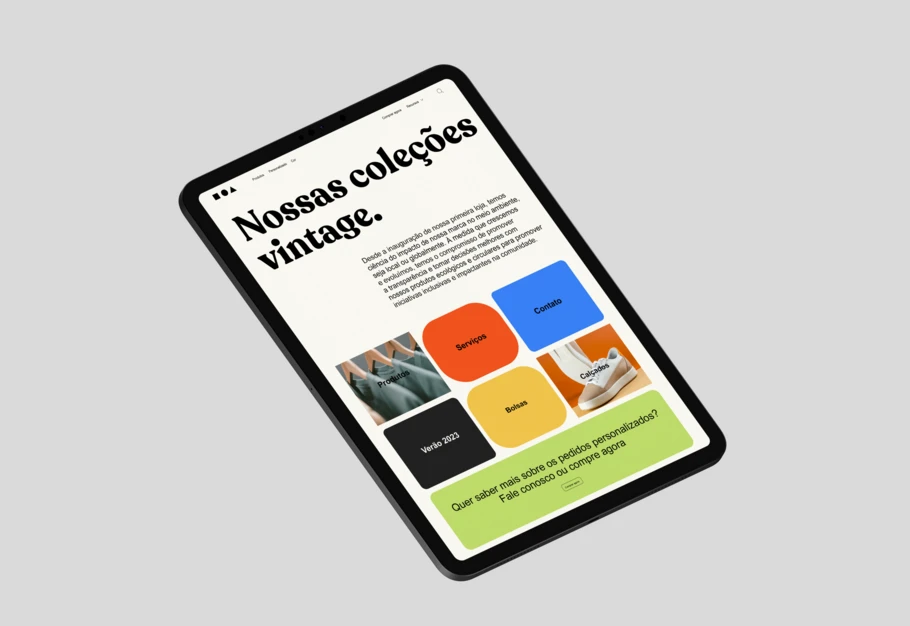
Sem confusão: cinco maneiras de manter sua marca prosperando na era digital.
À medida que os consumidores alternam entre telas grandes e pequenas, é fundamental que as marcas acompanhem essa dinâmica.
Sem confusão: cinco maneiras de manter sua marca brilhando na era digital.
Suas fontes de marca podem fazer a transição perfeita do ambiente físico para a Web? Suas fontes são legíveis em um aplicativo? E quanto a anúncios ou banners digitais? Ou um novo ambiente, como o metaverso, por exemplo?
Tornar a presença omnicanal de uma marca e a transformação digital coesas em todas as plataformas não é uma tarefa fácil, seja produzindo uma página da Web, um anúncio digital, um aplicativo, uma experiência de realidade virtual ou um novo jogo em uma arena virtual.
À medida que os consumidores alternam entre telas grandes e pequenas, é fundamental que as marcas acompanhem essa dinâmica. A escolha da fonte desempenha um papel fundamental. Afinal, uma presença de marca consistente em todos os pontos de contato mantém o nível de confiança alto e cria uma experiência agradável para o cliente.
Então, da próxima vez que você estiver trabalhando em um design para o mundo moderno, use esta lista de verificação para garantir que suas fontes estejam à altura da era digital – sem incertezas.
1. Verifique: É legível?
Se um designer encontra uma fonte perfeitamente legível em um dispositivo, pode não ser o caso em outro. Irritante? Sim. Solucionável? Também. Usar uma fonte nativa de um aplicativo ou ajustar o espaçamento de cada caractere até que fique perfeito no aplicativo de design ainda pode levar a incertezas, imprecisões ou até mesmo à desconfiança na marca. Os consumidores devem conseguir ler facilmente as fontes no mundo digital, seja em um aplicativo, videogame ou ambiente de realidade virtual. Escolher um tipo projetado para funcionar bem em todos esses formatos é fundamental.
2. Verifique: Velocidade do carregamento.
À medida que as marcas se conectam com os clientes no cenário digital, há um aspecto funcional a considerar: como aquela fonte gratuita que você encontrou aleatoriamente on-line está afetando seus tempos de carregamento? Se você está lidando com arquivos de fontes antigos, o que pode ser o caso, é provável que isso tenha um impacto negativo.
Os clientes não têm tempo para esperar e sairão de uma página da Web, mudarão para um novo aplicativo ou sairão de um jogo de videogame se demorar muito para carregar. Para evitar isso, encontre fontes que otimizem o desempenho do seu software de fontes. Com suas fontes sempre atualizadas do ponto de vista tecnológico, você nunca precisará se preocupar com o que está por sob a superfície.
3. Verifique: Redimensionamento.
De manchetes em um site ao texto na pequena tela de um smartwatch, usar texto dinâmico – isto é, texto que muda de layout ou parâmetros – deve ser uma prática padrão para qualquer experiência digital de marca. Já vimos isso se tornar comum na Web 2, à medida que muitos sites dinâmicos se adaptam facilmente de desktop para tablet e smartphone. Agora, as marcas precisarão pensar em como suas fontes aparecem em ambientes mais colaborativos e descentralizados, como Web 3, bem como em espaços de AR e VR.
Finalmente, se houver uma mudança em uma mensagem ou conceito, um designer (ou outro criativo de confiança) deverá ser capaz de fazer essa mudança rapidamente. Isso acontece o tempo todo em sites de notícias, atualizações de jogos ou mesmo em lojas de varejo ao se preparar para o fim do ano. Quase nada no espaço on-line é estático, e ter uma fonte dinâmica significa fazer mudanças eficientes e ágeis sem se preocupar com uma exibição ilegível.
4. Verifique: Problemas de renderização.
Outro aspecto funcional das fontes que não pode ser negligenciado: a renderização do texto. É um assunto complicado, especialmente quando se trata de desenvolvimento de aplicativos ou criação de outros ativos digitais que podem ter caracteres específicos. Problemas de renderização surgem quando há erros na capitalização, reordenamento de caracteres, formas incorretas ou direção errada. Isso pode se tornar particularmente desafiador com fontes em diferentes idiomas. Designers experientes conseguem perceber quando a renderização está errada; fontes pixeladas ou layouts pouco sofisticados são um grande problema para uma marca, e os clientes muitas vezes se perguntam o que está causando a dor de cabeça. Escolher uma fonte confiável com um conjunto completo de caracteres e scripts bem-desenvolvidos que renderizem sem problemas é o objetivo.
5. Verifique: Identidade da marca.
Até agora, cobrimos pontos funcionais e criativos que garantem texto claro, legível e de carregamento rápido em todos os dispositivos. No final das contas, tudo isso contribui para a representação da marca. Quando uma fonte disponível para impressão não é otimizada como fonte da Web, os designers têm que fazer uma escolha difícil com uma fonte da Web que não está à altura. Às vezes, eles conseguem lidar com isso, e outras, é um desastre. Uma experiência de marca inconsistente, do físico ao digital, cria um efeito de “Vale da Estranheza” na mente do consumidor: subconscientemente (às vezes conscientemente) isso gera desconfiança ou uma sensação de menor empatia ou identificação com a marca.
As marcas podem evitar esse problema escolhendo uma fonte que funcione de forma idêntica nos ambientes físico e digital desde o início, especialmente sabendo que estamos mergulhando de cabeça em um futuro de realidade mista (metaverso, estamos olhando para você.) Conclusão? Seu trabalho como designer é garantir que não haja quebras na experiência da marca: e as fontes desempenham um papel crítico.
Lista de verificação de fontes para produtos digitais.
• Legíveis
• Carregamento instantâneo
• Dinâmicas
• Pixelização impecável
• Alinhadas com a marca